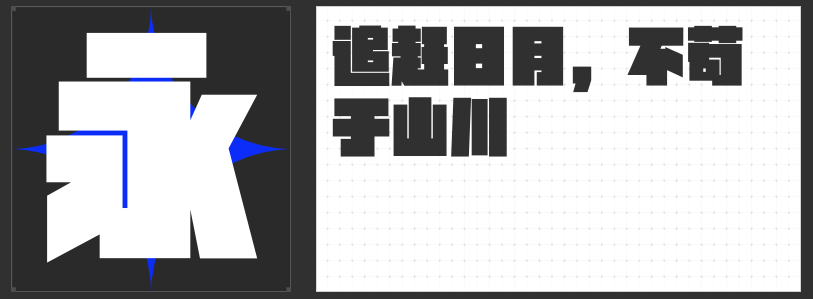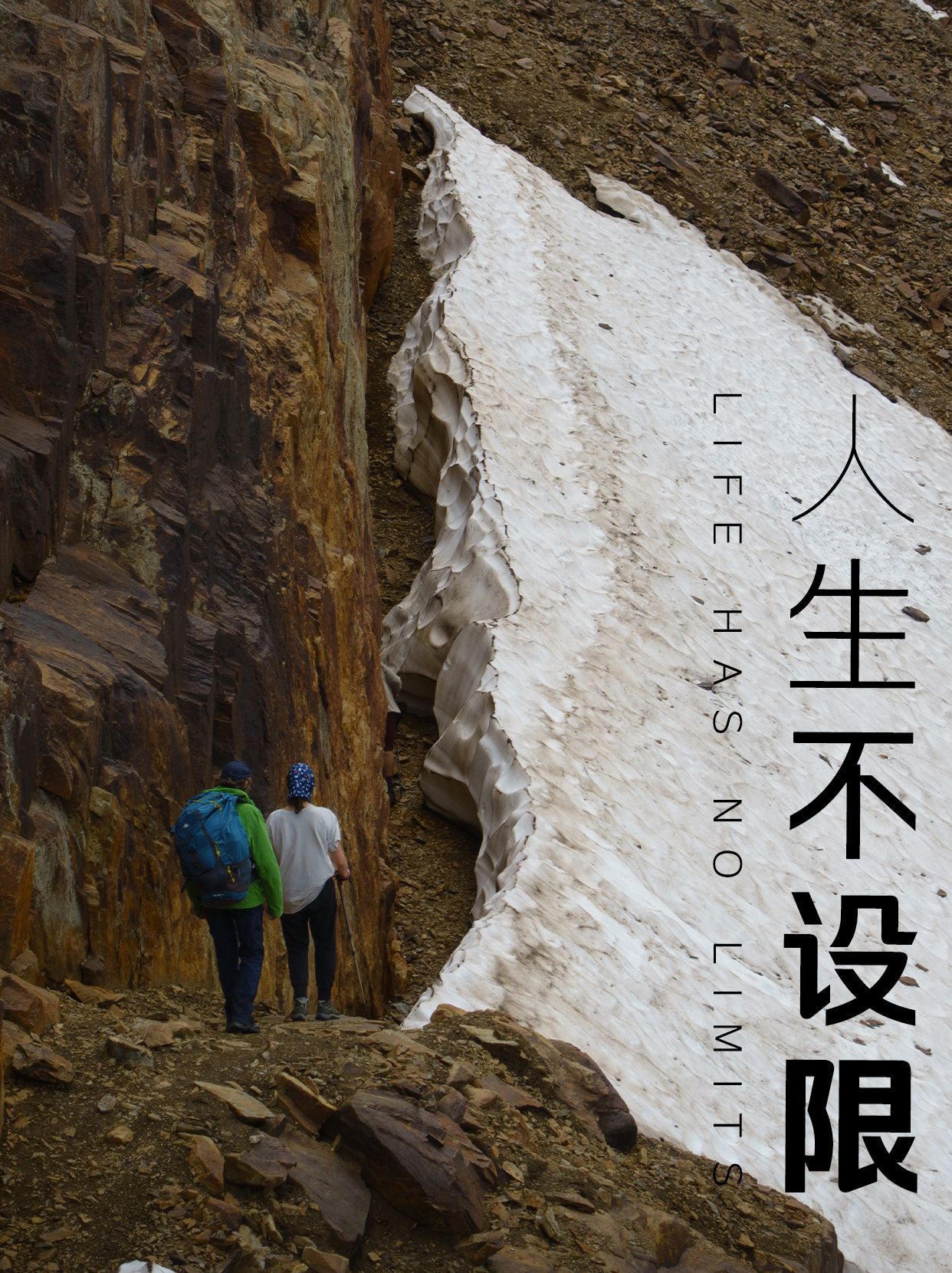
现代简约之美:精选字体推荐,打造视觉新风尚
在数字化时代,字体不仅是信息传递的载体,更是视觉美学的展现。现代简约字体,以其清晰、利落、不张扬的特点,成为了设计领域的宠儿,广泛应用于品牌标识、网页设计、UI界面及印刷品等多个领域。今天,就为大家推荐几款备受青睐的现代简约字体。
在追求极致简约与力量感的今天,励字铁拳简 超级黑以其独特的魅力脱颖而出。这款字体融合了现代简约的设计理念与铁拳般的硬朗风格,每一个笔画都透露出不容忽视的力量与决心。它不仅适用于品牌标识、广告标语等需要强烈视觉冲击力的场景,更能为设计作品增添一抹不凡的个性与深度。选择励字铁拳简 超级黑,让您的设计更加鲜明、有力,引领现代简约新风尚。
引领设计潮流,励字开拓者简 超级黑以其独特的现代简约风格,成为设计师们的挚爱。这款字体简洁而不失力量,每个字符都散发着开拓者的勇气与决心。它不仅在视觉上带来强烈的冲击,更蕴含了不断探索、勇于创新的精神内涵。无论是品牌宣传、广告海报还是UI设计,励字开拓者简 超级黑都能完美融合,为您的作品增添一抹不凡的亮色。
在简约设计的浪潮中,励字暴风简 超级黑以其独特的暴风般的力量感,脱颖而出。这款字体将简约与力量完美融合,每一笔一划都仿佛蕴含着风暴的力量,既清晰易读又不失震撼力。它适用于追求视觉冲击力与个性表达的现代设计项目,如品牌标题、广告标语等,让您的设计作品在简约中展现非凡的气势与张力。
在简约与力量的平衡中,励字超级勇士简 特细以其独特的特细笔触,展现了勇士般的坚韧与细腻。这款字体将现代简约设计理念与勇士精神巧妙结合,虽细却有力,既保持了文字的清晰可读性,又赋予了作品一种独特的韵味与深度。它适用于需要展现精致与力量并存的设计场景,如高端品牌文案、艺术展览标题等,让您的设计在简约中彰显不凡品味。
这些现代简约字体,不仅提升了设计作品的整体质感,也反映了当代社会追求简洁、高效、国际化的审美趋势。无论是专业设计师还是普通用户,都能在这些字体中找到适合自己的风格,让设计作品更加出彩。